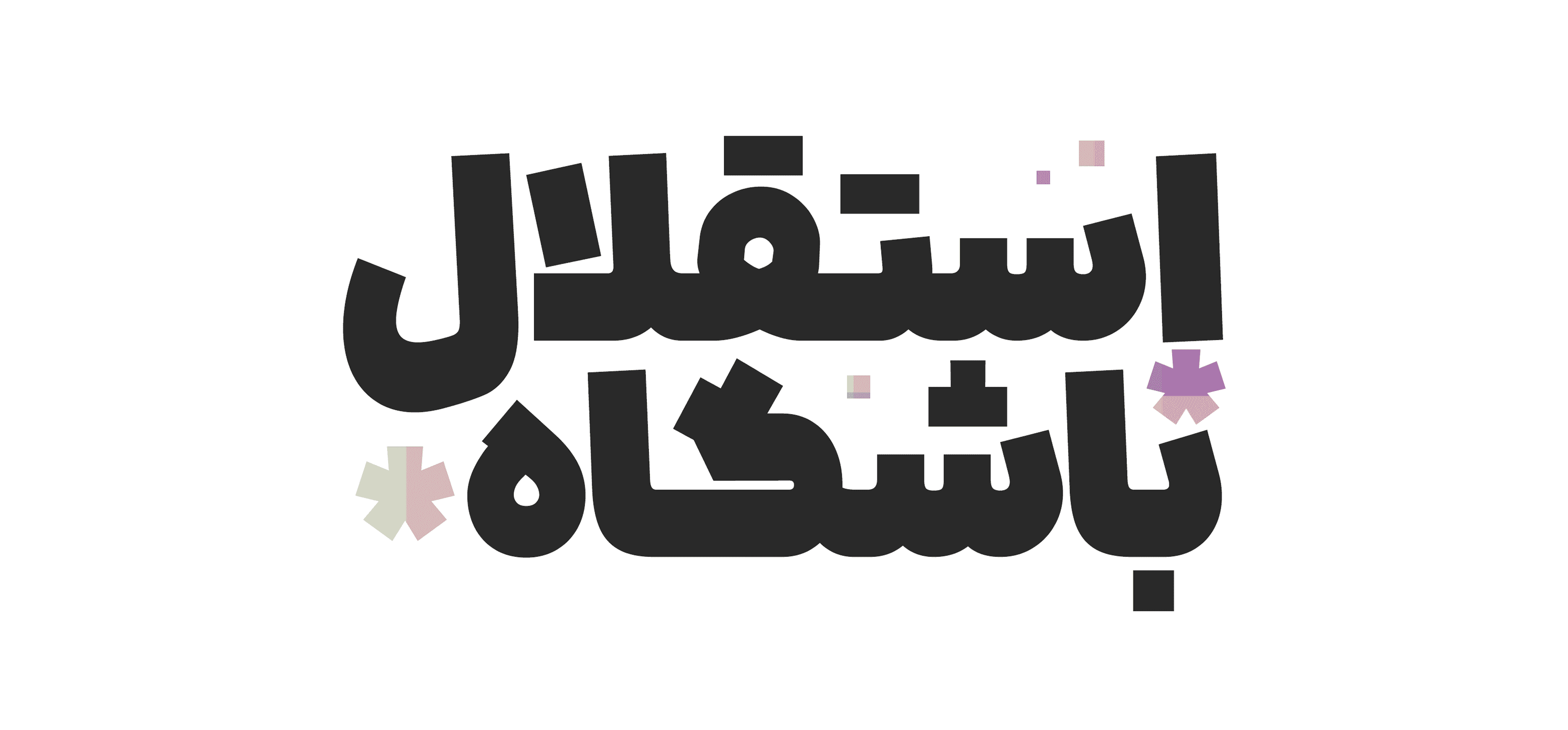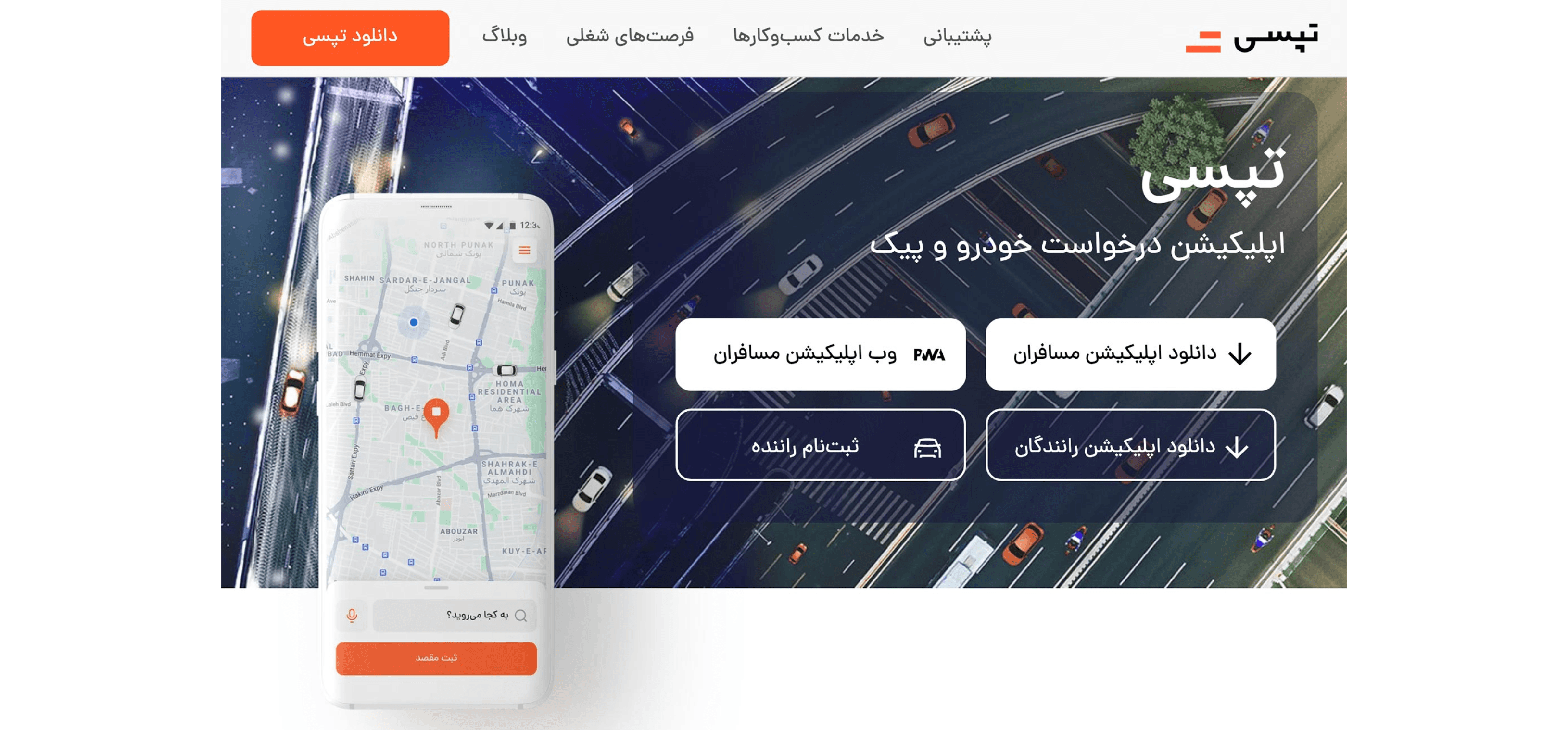
خط "دانا" هو محاولة لابتكار خط طباعي يجمع بين الطابع الهندسي وقواعد خط النسخ.
الطابع الهندسي يمنح خط دانا مظهرًا عصريًا وحديثًا، بينما يُسهم الالتزام بأسلوب النسخ في الحفاظ على وضوح القراءة في الأحجام الصغيرة والنصوص الطويلة.
تم إصدار خط دانا لأول مرة في شهر خرداد عام 1398 (يونيو 2019)، ومنذ ذلك الحين أصبح محبوبًا بين مصممي المنتجات.
اعتمدت العديد من العلامات التجارية والأعمال الناشئة على خط دانا لتحقيق تصميم عصري ومعاصر.
في أسفل هذه الصفحة، يمكنك مشاهدة عدد من هذه التصاميم كمثال على استخدام الخط.